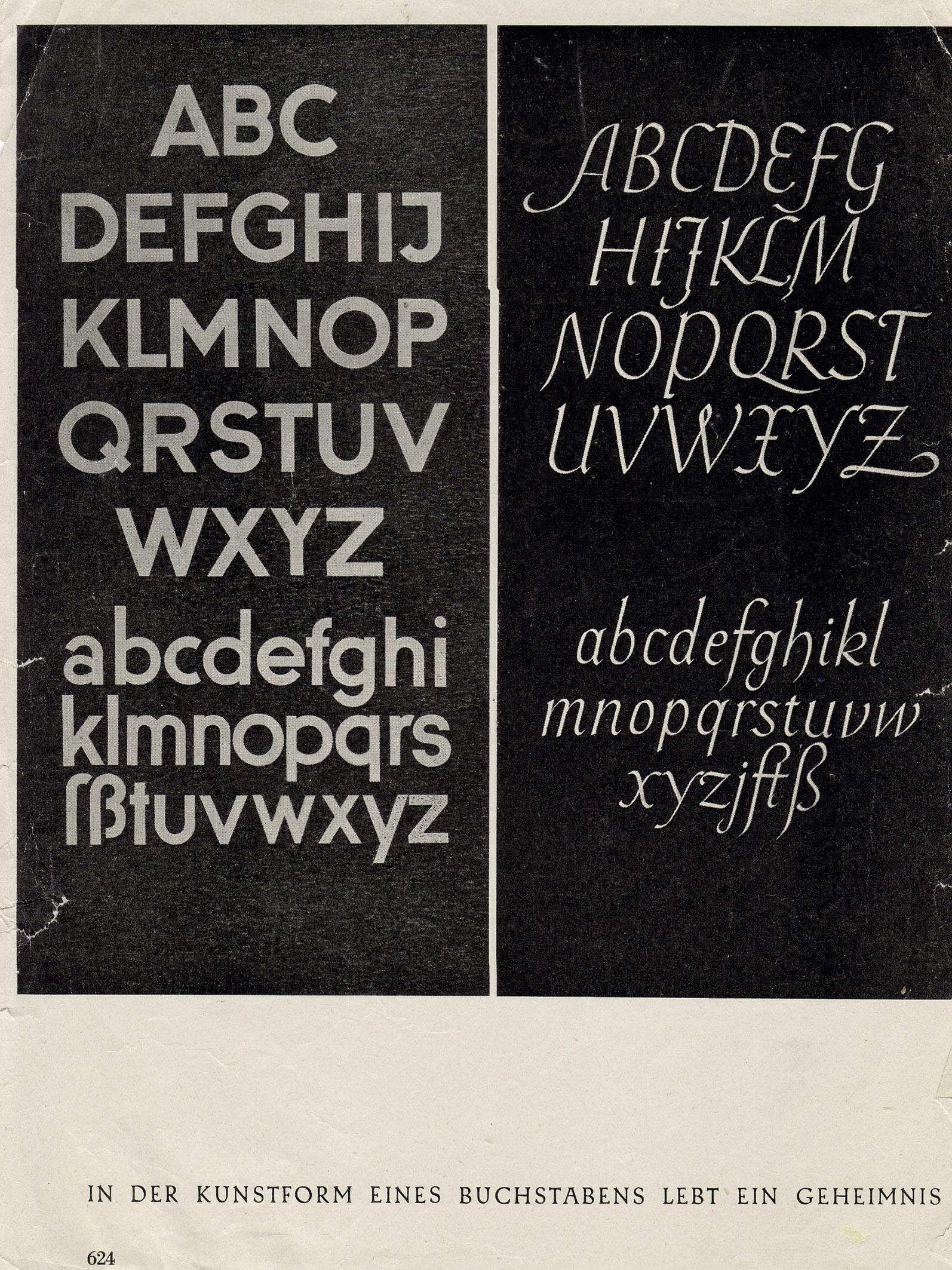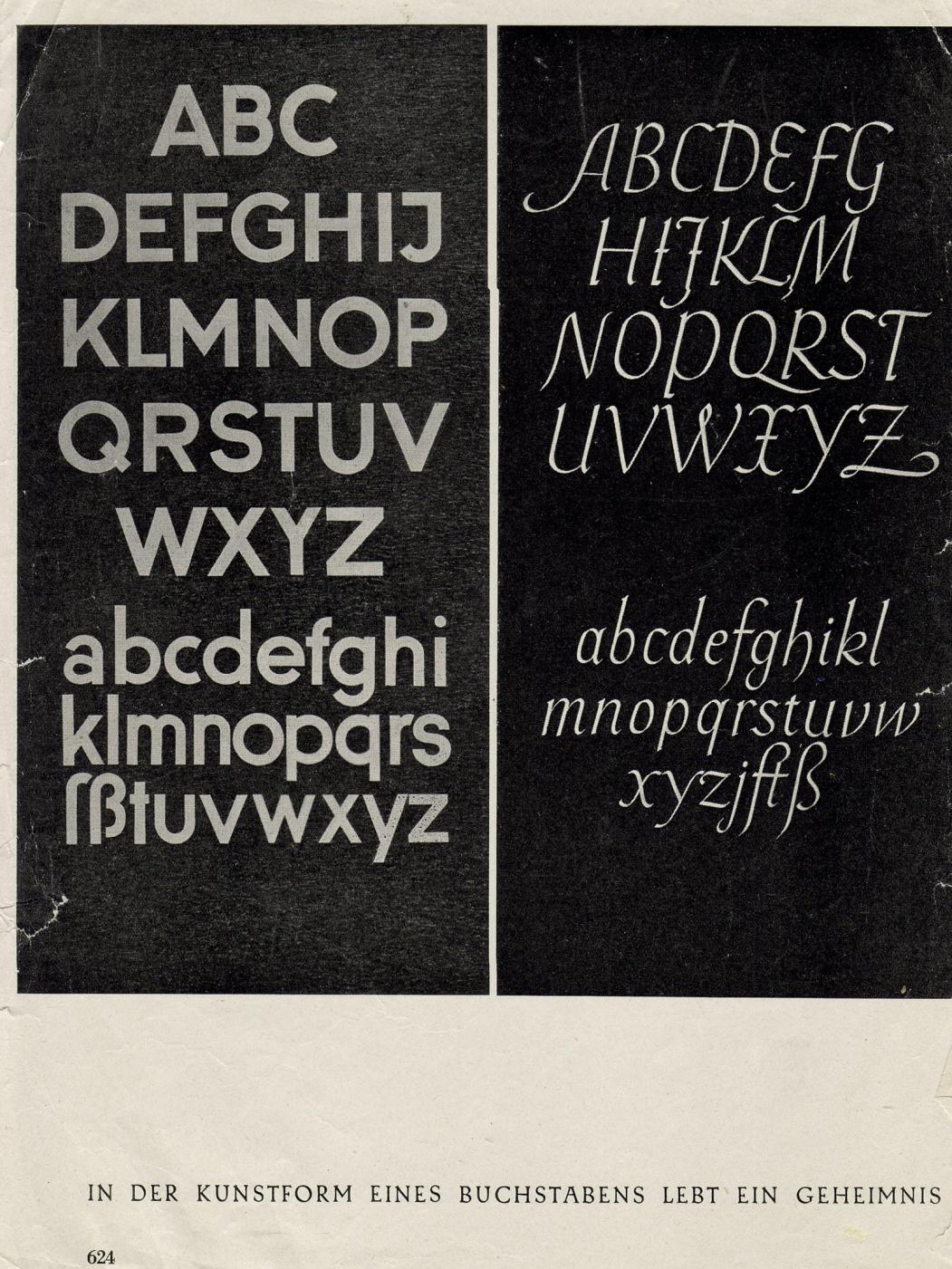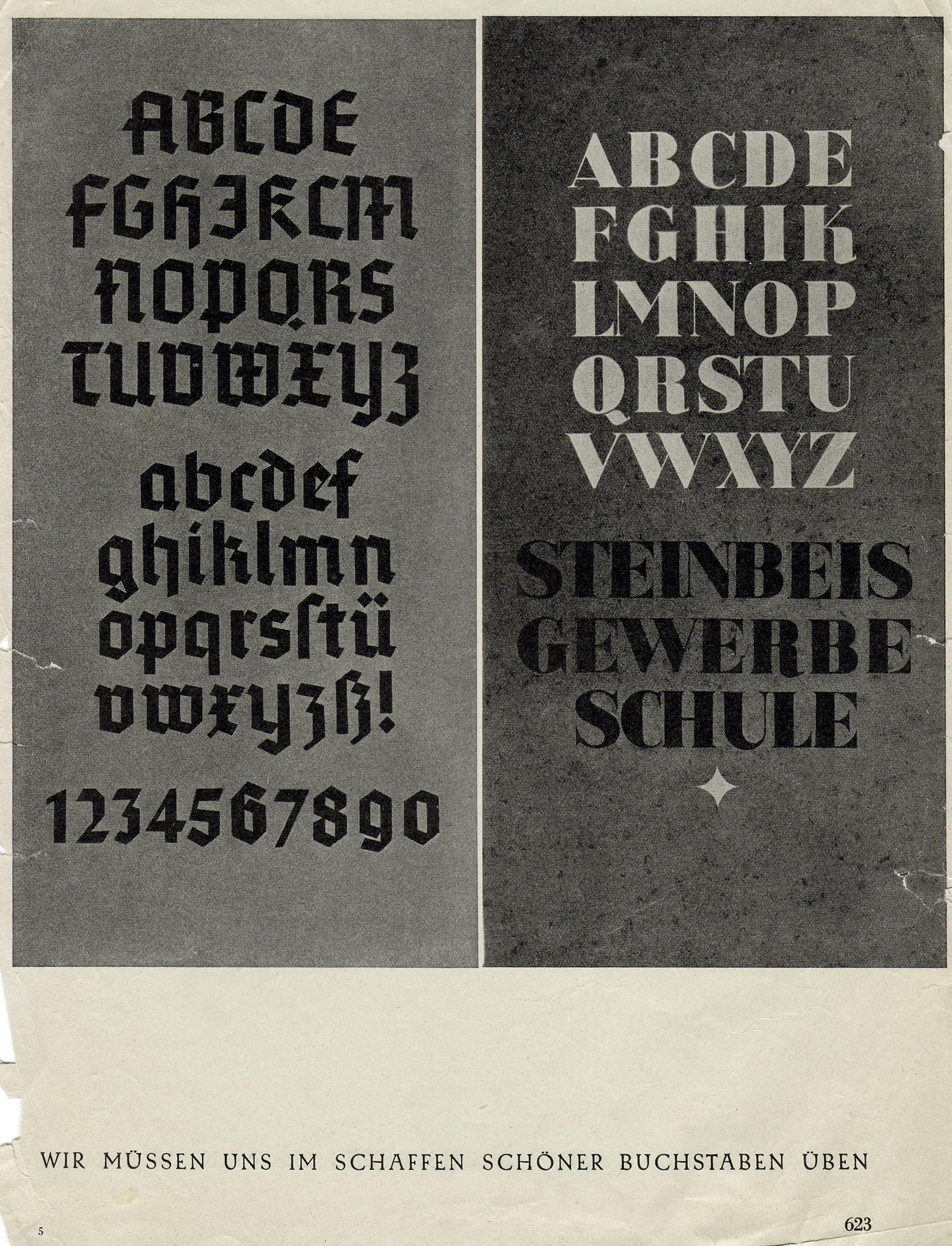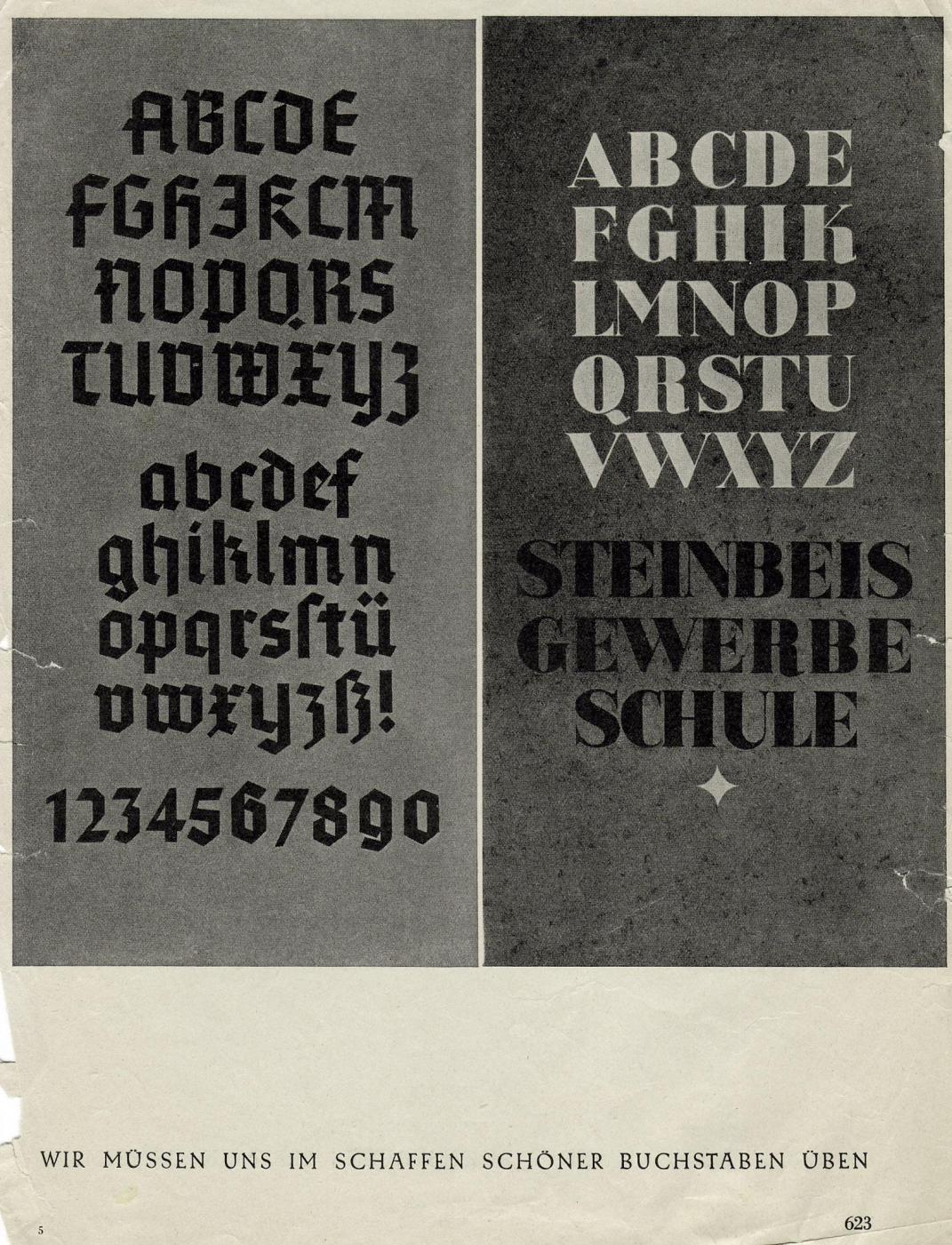
Ausschnitte aus einer alten Fachzeitschrift
Das wird eventuell dem Umstand geschuldet sein, dass das der Zeitschrift "Der Maler" entspringt – für Beschriftungen sind Unterlängen eher hinderlich.
Was mich aber wundert: Die "j" und die meisten "J" fehlen – welchen Grund mag das haben?
Und noch etwas Öl ins Feuer: Die
STEINBEIS
GEWERBE
SCHULE
kommt ganz ohne Bindestrich aus … :shock:
Dieses Argument sticht überhaupt nicht, da in der gleichen Vorlage bei g, p, q und y Unterlängen vorhanden sind, sowie auch in den anderen Mustertafeln. Bei vertikal begrenztem Raum können Unterlängen gelegentlich problematisch sein, aber das ist nie und nimmer eine allgemeingültige Einschränkung.
Da soll auch nix stechen, deswegen habe ich den Konjunktiv sogar noch mit einem "eventuell" ergänzt.
… und damit ergibt der entsprechende Satz noch viel weniger einen Sinn.
Für dich mag das keinen Sinn ergeben.
»Der Maler« spricht von »Buchstaben«, nicht von Satz auf einer Grundlinie, und zeigt daher einzelne Buchstabenformen und keinen Satz auf einer Grundlinie. Wir sehen noch nicht mal ein Alphabet mit aufeinander abgestimmten Buchstaben – das o ist zu groß etc.